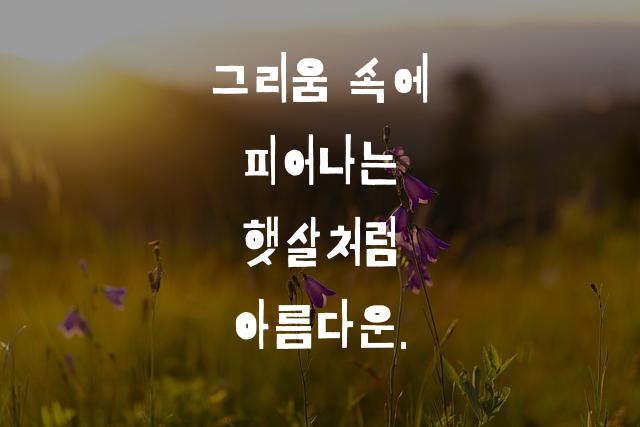
꾸불림체는 우아한형제들에서 제작한 폰트로, 그 이름처럼 독특하고 삐뚤빼뚤한 매력을 지녔습니다. 이 폰트는 감성적이면서도 개성 있는 디자인을 선호하는 이들에게 적합합니다.
꾸불림체은(는)
계열의 생김새를 가지고 있으며
어린이 책, 초대장, 인사말 카드 등에서 자주 활용되며, 효과적인 메시지 전달에 적합합니다.
이 폰트는 문화/예술, 이벤트/웨딩, 유아/가족 분야에 잘 어울리며,
친근한, 귀여운, 재미있는 느낌을 담고 있는 것이 특징입니다.